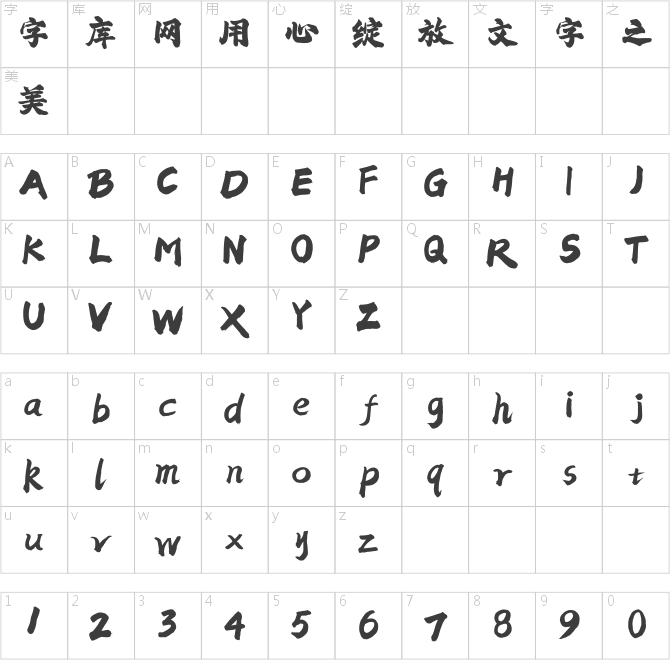
毛筆
字庫創(chuàng)作歷時一年時間,完成共7千多字,滿足當(dāng)今商業(yè)化應(yīng)用的需求。字體風(fēng)格穩(wěn)重, 氣勢上揚,筆畫厚重有力是此套字庫的特點。適用于各種標(biāo)題大字排版,電影海報、包裝、 電商、品牌名稱、漫畫、影視綜藝、游戲、各類商業(yè)海報、戶外廣告標(biāo)題等。